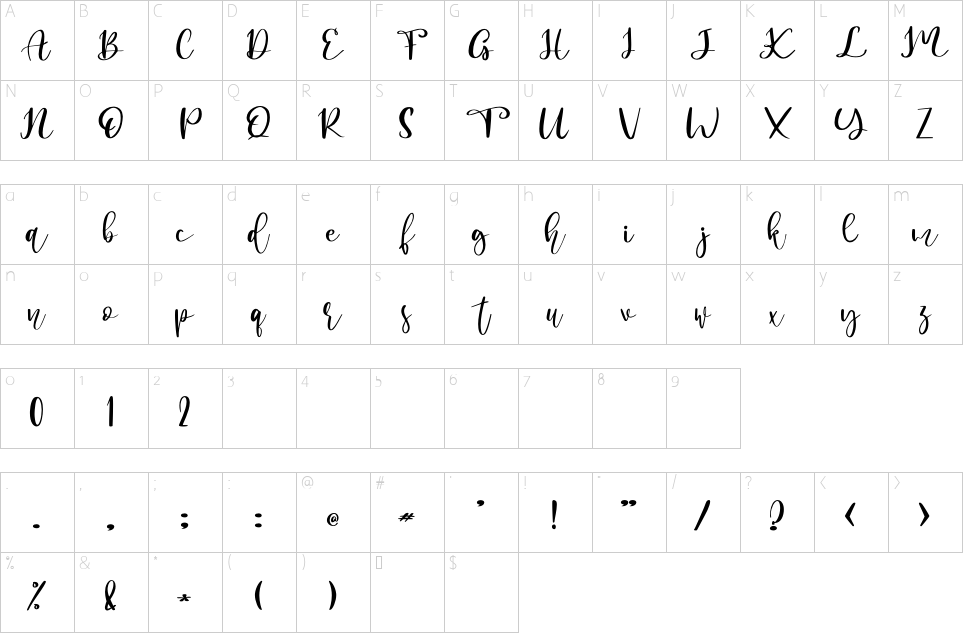
Descubra a fonte Gatra Std, uma escolha ótima para projetos criativos que valorizam simplicidade e elegância. Desenvolvida pelo designer wahyu edhi widodo, essa font é perfeita para web designers, desenvolvedores de sites, até mesmo quem deseja personalizar documentos. Com um design minimalista mas sofisticado, a Gatra Std é uma opção versátil que combina bem com vários estilos de escrita e gráficos. Ela foi popular entre os usuários do Windows e Mac, sendo baixada 1.549 vezes. Sua simplicidade perfeita, combinada à beleza elegante da fonte, a torna uma escolha inteligente para projetos digitais onde um toque de classe pode fazer toda a diferença. Descubra agora a Gatra Std e transforme seus projetos em algo realmente especial.